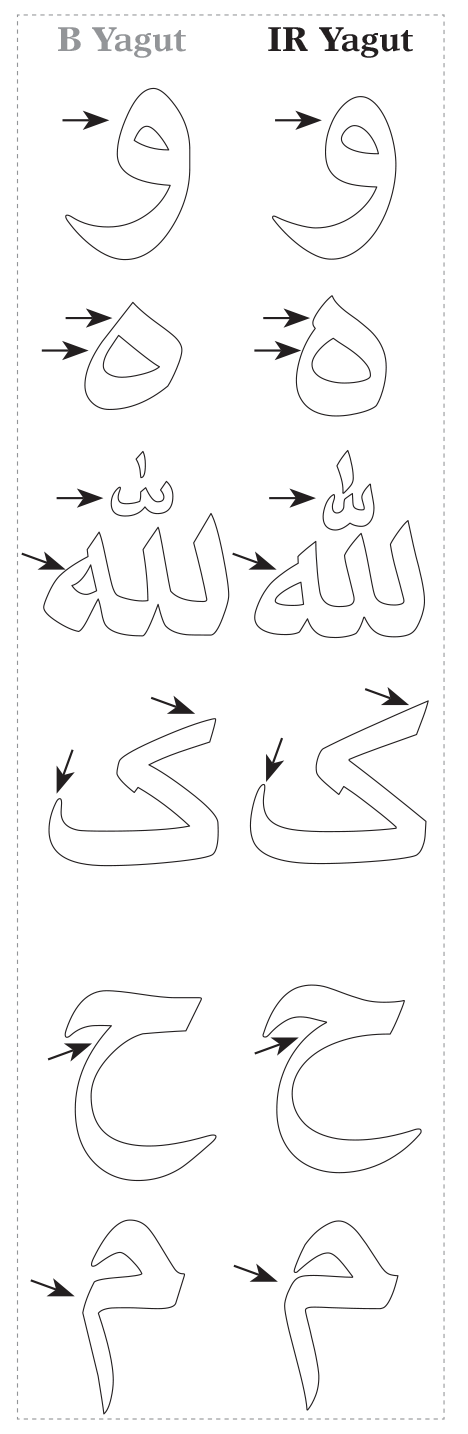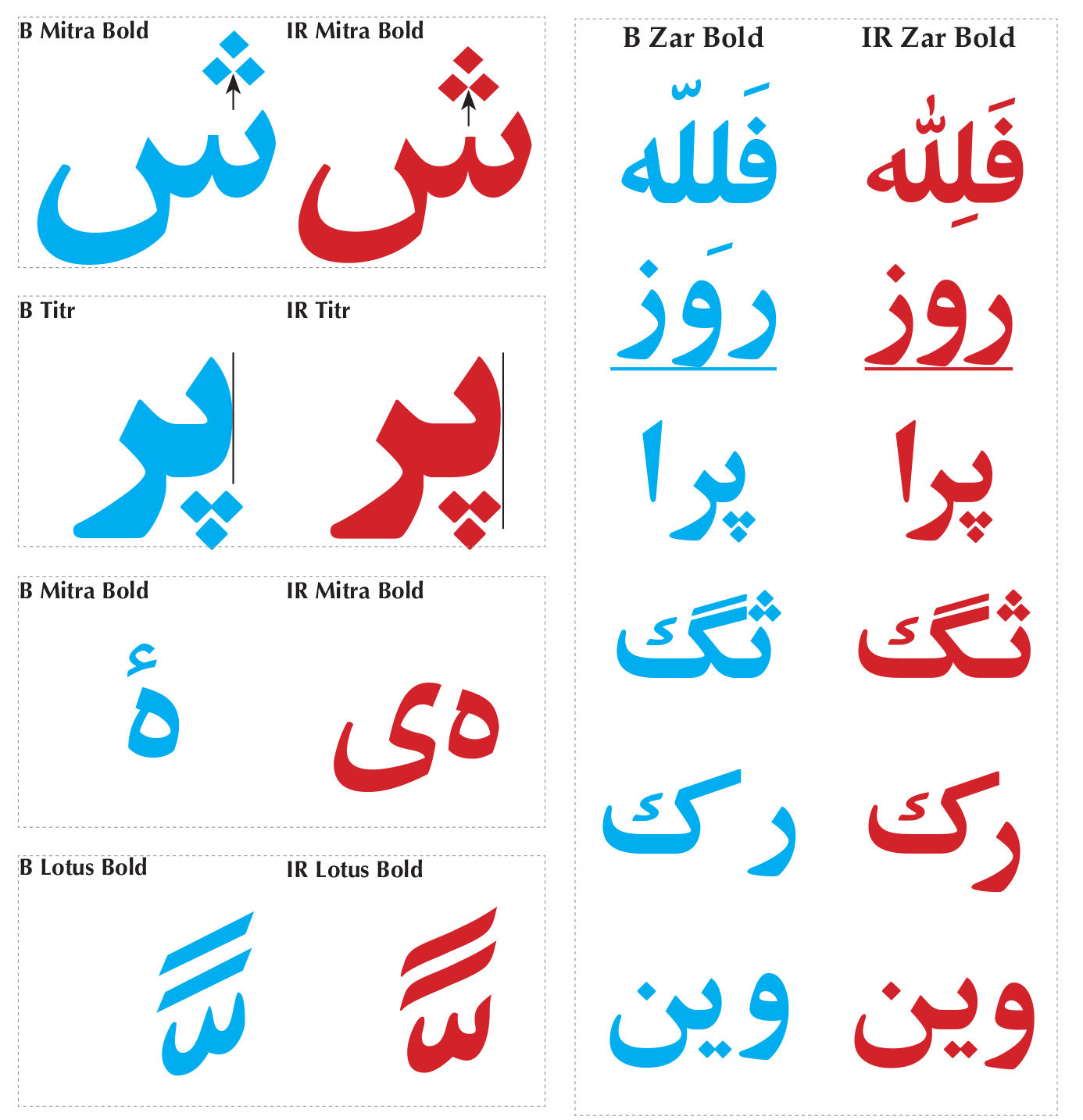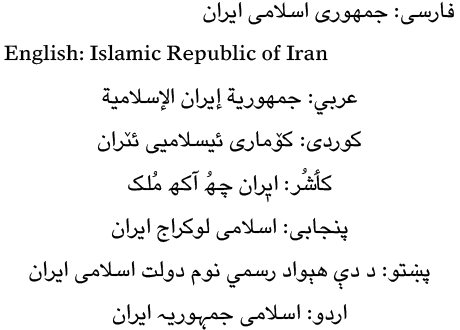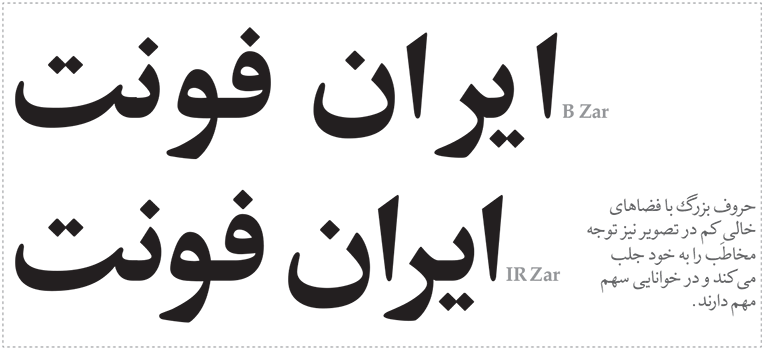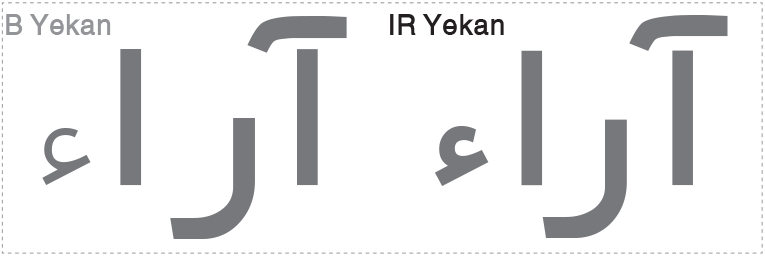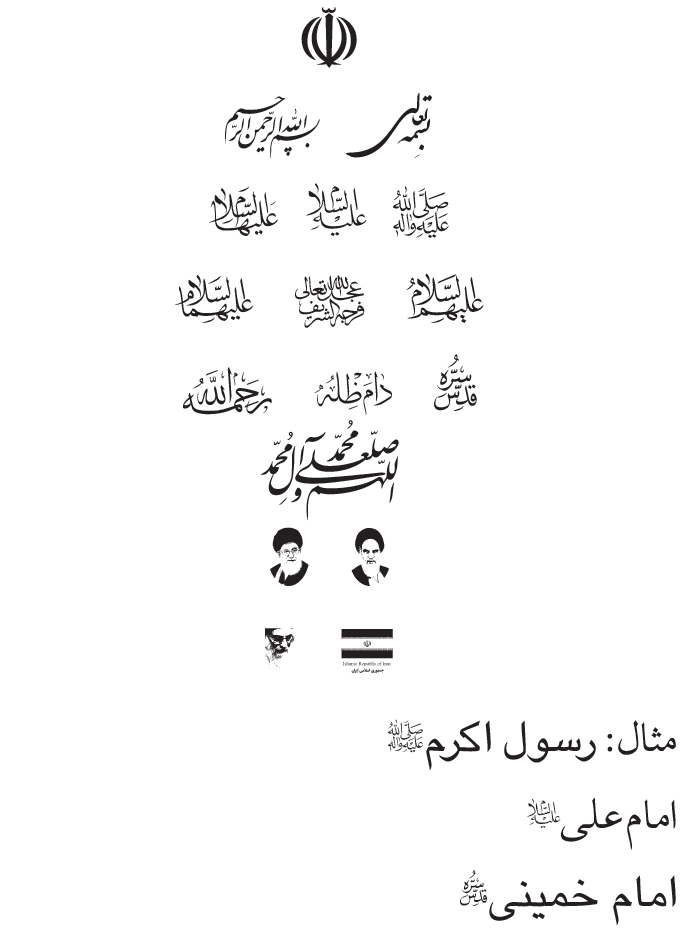
فونت‌های فارسی اغلب در انطباق با استانداردهای ملی و بین‌المللی و همچنین از نظر قواعد زیباشناختی، کاستی‌های بسیاری دارند. از این رو ایران فونت، اصلاح و استاندارسازی 40 فونت فارسی را در دستور کار قرار داد. و پس از اعمال اصلاحات زیر در بسته جامع ایران فونت گردآورد. که در ادامه به موارد اصلاح و یا بازسازی شده اشاره خواهیم کرد.
از مهم‌ترین ویژگی‌ فونت‌های اصلاح شده می‌توان به تنظیم درهم‌رفتگی (kerning) حروف و کاهش حداقل 10 درصدی طول متن اشاره کرد که در کنار افزایش زیبایی متن، کاهش حجم صفحات یک کتاب، کاهش مصرف کاغذ و هزینه را موجب می‌شود. در این رابطه توصیه میکنیم به تصاویر زیر خوب دقت کنید:
پشتیبانی از نیازهای خاص زبان‌های هم‌خانواده فارسی مانند عربی، پشتو، اردو و کردی نیز از دیگر ویژگی‌ فونت‌های اصلاح شده محسوب می‌شود که با چنین رویکردی شاهد نفوذ فرهنگی در کشورهایی که از این زبان‌ها استفاده می‌کنند، خواهیم بود. برای نمونه یک جمله را فونت یاقوت به چندین زبان در تصویر زیر نمایش داده می‌شود:
اصلاح حروف: در این مرحله به تک تک حروف بعنوان شخصیتی منفرد توجه شده و اصلاحات مورد نیاز روی آنها اعمال گردید. از جمله این اصلاحات موارد زیر را می‌توان بیان کرد:
• رفع شکستگی‌ها و اعوجاج موجود در منحنی حروف. این اشکال مخصوصاً در اندازه بزرگ نوشته‌ها نمایان بود.
• بسیاری از حروف ظرافت‌هایشان، به مرور از بین رفته بود که در این مرحله سعی شده این ظرافت‌ها برگردانده شود.
• متناسب‌سازی هر حرف از نظر اندازه و شکل با سایر حروف
• تعیین محل مناسب برای نقاط و اعراب
درج آسان و دسترسی راحت به جملات دعایی کارکترهای پرکاربرد و محبوب با فشردن کلید Alt و اعداد 1 تا 18 و یا از طریق Character Map:
تصحیح محل اعراب، امکان درج فونت در فایل‌های PDF، مطابقت با آخرین نسخه استاندارد یونی‌کد، استاندارد ملی 6219، استاندارد‌ Adobe Glyph Naming ، استاندارد  Open Type نیز در 40 فونت فارسی انجام شده است.
بالاخره اصلی ترین محصول ایران فونت (که وعده اش را داده بودیم) عرضه شد. و این یعنی حدود 750 فونت فارسی بدون تکرار. و این یعنی تحولی در عرصه نگارش فارسی. این بسته منحصر به فرد که برخی از ویژگی‌هایش در ادامه ذکر خواهند شد در دهه سوم شهریور ماه منتشر شد. تا همگی به این باور برسیم که خط فارسی بسیار زیباتر از آن است که در چند ده فونت سالهای پیش خلاصه شود.
حقیقتا کار بزرگی صورت گرفته است. صرف 3 سال زمان و انرژی و بررسی هزاران فونت این رسم الخط از سراسر جهان، جمع آوری، بازبینی، گلچین و اصلاح و ارتقای آنها اتفاق کمی نیست که بتوان به سادگی از آن گذشت. خروجی این کار بسته ایران فونت (بانک قلم‌های ایرانی) شده است. که به اعتقاد ما با توجه به قابلیت‌های منحصر به فرد این بسته، حرفه‌ای بودن، جدید، جامع و یکپارچه بودن؛ بهترین بسته‌ی فونتی خواهد بود که تا حال حاضر به بازار عرضه خواهد شد. این تنها یک بخش از محتویات بسته‌ی جامع فونت فارسی است.
1. بسته جامع فونت فارسی
حدود 650 فونت فارسی ویرایش و بازسازی شده + حدود 25 فونت جدید انحصاری (از قبیل فونت پرشین گلف). پیشوند تمامی این فونتها B می‌باشد تا از بهم ریختگی در نوار فونت‌های شما خودداری گردد و بصورت یکپارچه در کنار هم قرار گیرند. با داشتن این بسته مطمئن خواهید بود که بدون استثنا تمامی فونت‌هایی که در سراسر محصولات فارسی و فارسی‌نویس‌ها وجود دارند را خواهید داشت. توضیحات بیشتر
2. بسته حرفه‌ای فونت فارسی
این بسته 45 گانه با پیشوند ir شامل فونت های حرفه ای است که از قابلیت‌های بسیار ویژه برخوردار هستند. برخی از این ویژگی ها را در زیر ذکر می کنیم:
الف: پشتیبانی از تمام حروف فارسی، اردو، عربی، انگلیسی
ب: پشتیبانی از کارکترهای خاص بطور ویژه همچون علیه السلام و...
ج: پشتیبانی از تکنولوژی های جدید فونت فارسی و همچنین کرنینگ (فرورفتگی حروف)
3. بسته فونت های خطی
بسته ای شامل 20 فونت خطی منحصر به فرد و پرکاربرد (تصویر). که از مهمترین آن میتوان به فونت شکسته نستعلیق، نسخ، ثلث، معلی و... اشاره کرد.